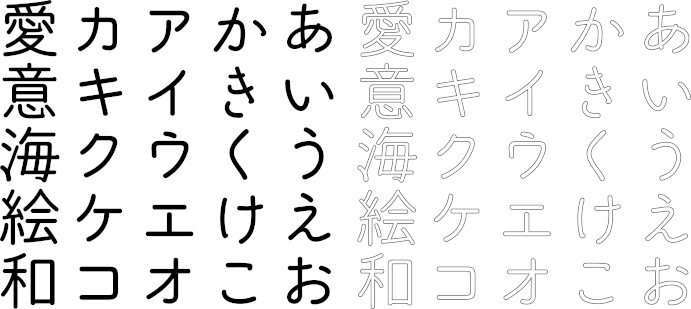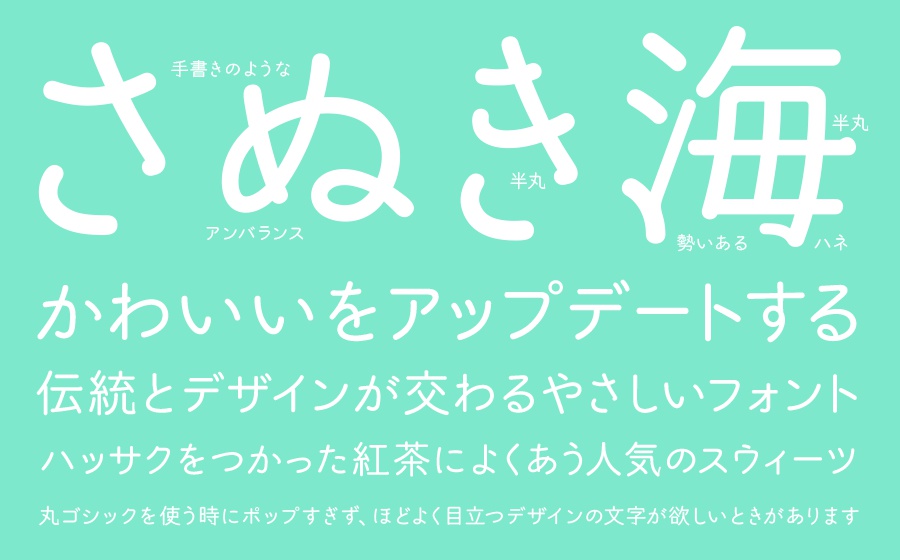
まるがめ本丸ゴシック - 2フォントSET
丸亀城のある、風光明媚な丸亀市をイメージした可愛い丸ゴシック体です。丸ゴシック体で可愛いデザインといえばポップでモダンな書体が多いのですが、逆に少し物足りないようなポチッとした可愛さを追求しました。手書きのようなやさしさでレトロな懐かしい雰囲気、そして独特の余白が今までとは違う可愛さを表現します。 幅広い環境に対応するためTrueTypeも同梱しています。おまけ特典として白抜き文字のまるがめ本丸ゴシックうどんが付いてきます。 収録フォント(2書体) まるがめ本丸ゴシック(レギュラー)、まるがめ本丸ゴシックうどん(白抜き) 動作環境 Mac:システム/OS X対応(10.x)〜最新のOS X Windows:OS/日本語版Windows2000、XP、VISTA、Windows7〜11以降 フォント形式:OpenTypeフォント、TrueTypeフォント 収録文字数について 収録文字数4,072文字(第一水準2965文字+第二水準460文字+ひらがな.カタカナ.約物.記号.アルファベット等647文字) 安心して使えるロイヤリティフリーの書体 あらゆる商用・デザイン用途(印刷物・ゲーム・アプリ・映像・動画・ロゴ・同人作品)に使用できる、商用申請の必要のないロイヤリティフリーの書体になります。文字の加工・変形も可能です。ご安心ください。